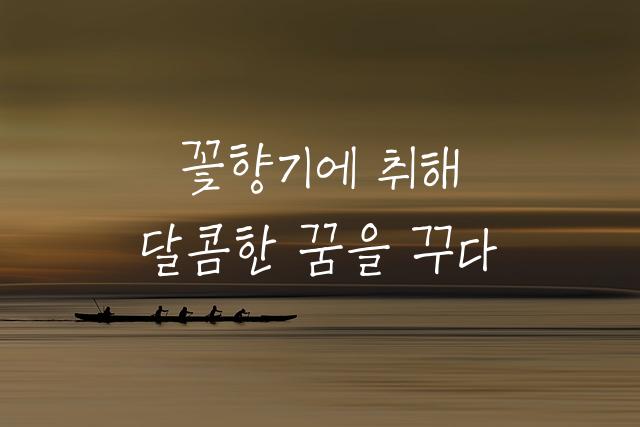
칠곡할매 이종희체는 한국 칠곡군에서 제작된 어른의 손글씨 스타일 폰트입니다. 따뜻한 감성과 친근한 느낌을 전달하는 이 폰트는 세심한 디테일과 개성 있는 필체가 특징입니다.
칠곡할매 이종희체은(는)
손글씨, 감성적인, 부드러움 계열의 생김새를 가지고 있으며
어린이 책, 인사말 카드, 일기/편지 등에서 자주 활용되며, 효과적인 메시지 전달에 적합합니다.
이 폰트는 라이프스타일, 문화/예술, 유아/가족 분야에 잘 어울리며,
따뜻한, 친근한, 편안한 느낌을 담고 있는 것이 특징입니다.